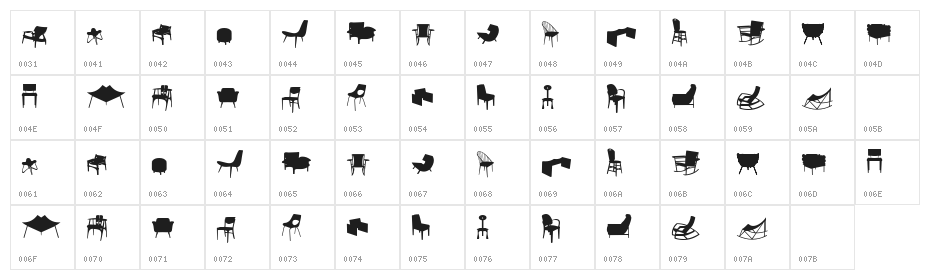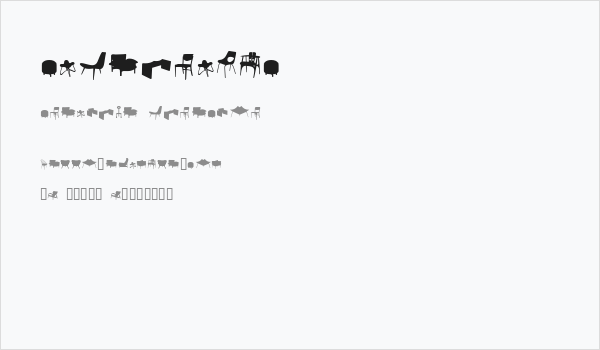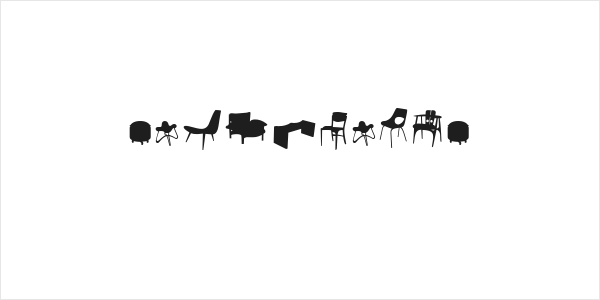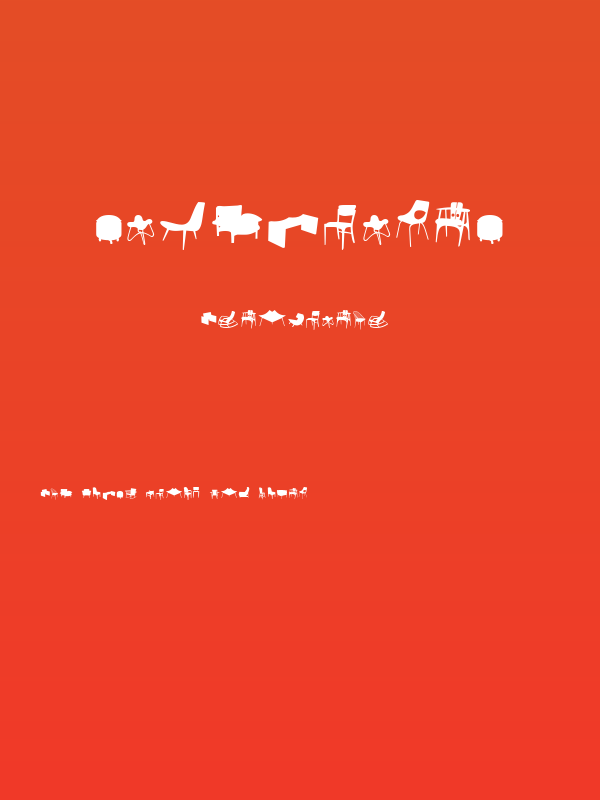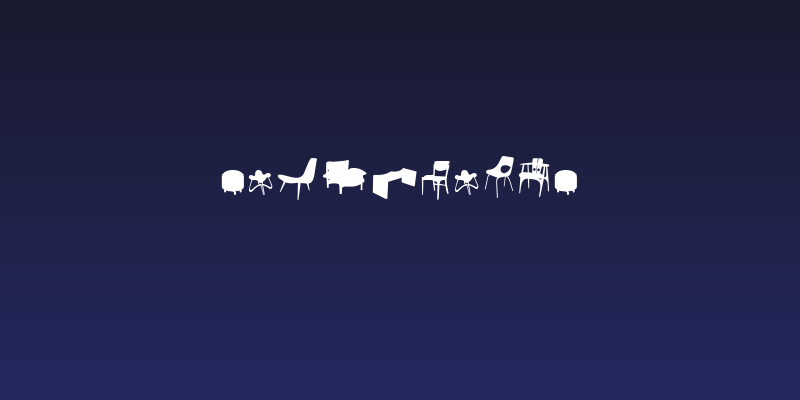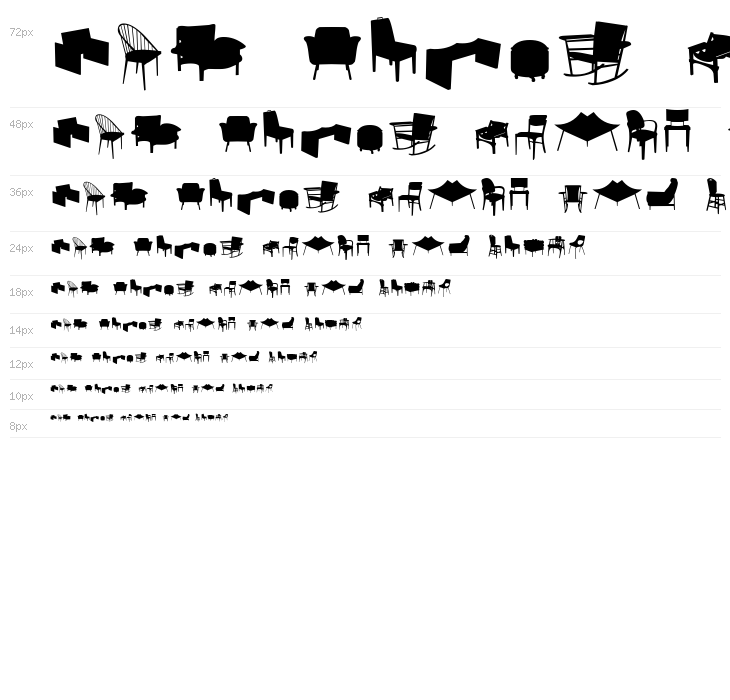
CadeirasPC Font
✎ Dingbats
| Gesamtstil | Decorative, Playful, Modern |
| Anwendungsfall | Icons, Decorative elements, Thematic branding |
| Vorgeschlagene Projekte | Interior design presentations, furniture catalogs, posters, branding for furniture stores, playful editorial layouts. |